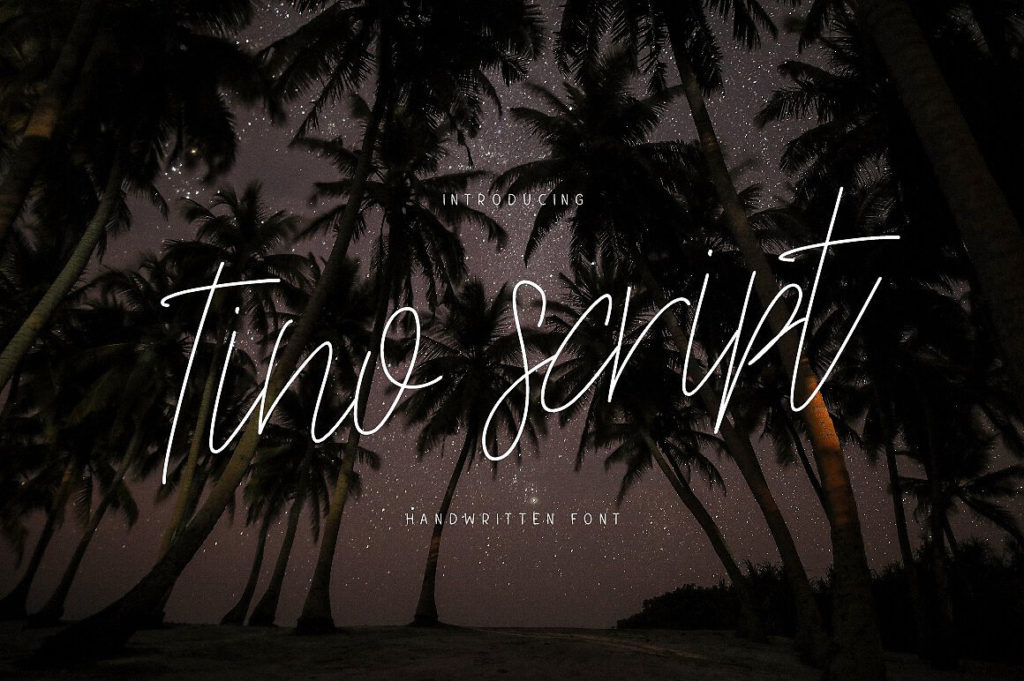
Шрифт Tino Script — это современный рукописный (script) шрифт с изящными линиями, выпущенный студией chekart в 2017 году. Отличается плавными, элегантными формами и аккуратным почерком, который придаёт тексту утонченный и романтичный вид. Буквы имеют тонкие, воздушные штрихи с изящными росчерками, что делает шрифт идеальным для проектов, требующих изысканности и «ручного» ощущения. Поддерживает кириллицу и латиницу, что позволяет использовать его в проектах на русском языке, где нужна элегантная и неформальная типографика. Если вы ищете стильный шрифт для особых проектов, вы можете ознакомиться с ним на этой странице.